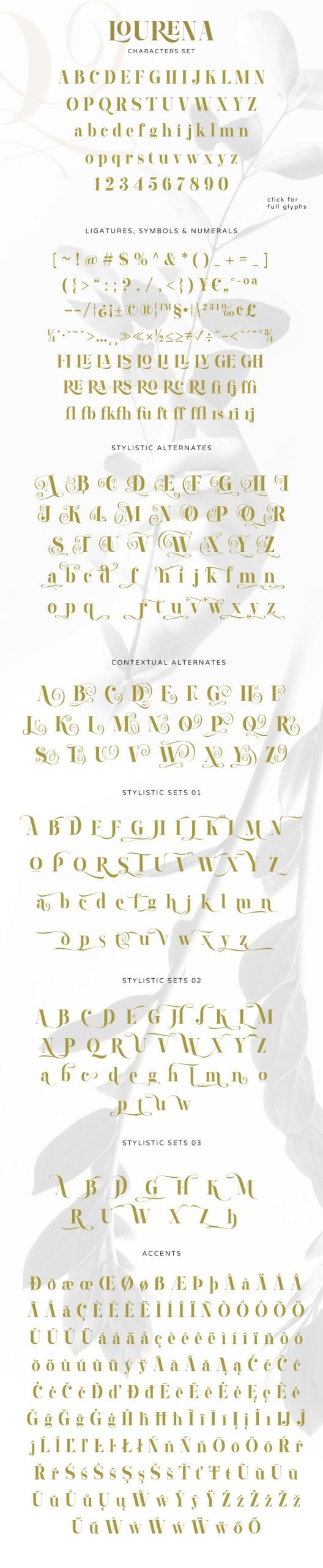
Font Lourena Việt Hóa – Kiểu font thư pháp
Lourena Việt Hóa, font chữ serif thời trang với nhiều tính năng bổ sung. Một bộ font chữ thanh lịch lấy cảm hứng từ đồ họa và thư pháp trang nhã mà bạn có thể sử dụng trên nhiều thiết kế.
Font chữ này được thiết kế với vẻ ngoài sang trọng, hiện đại và tối giản, rất tốt cho việc sử dụng biên tập, cũng trông hoàn hảo để kết hợp trong các font chữ viết tay hoặc chữ ký.